Caracteres nova-iorquinos
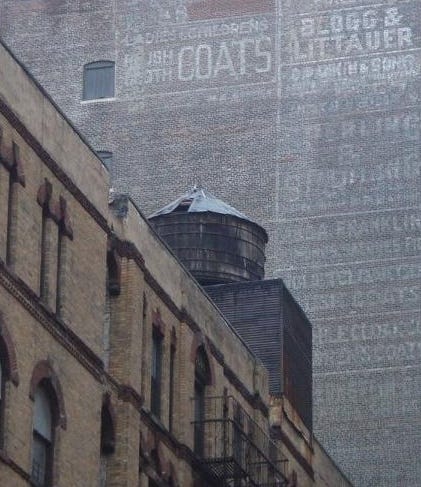
O blog New Type York fica catalogando 'artefatos tipográficos' de Nova York. São sinalizações de rua, nomes de prédio, placas de rua. O que for, onde for, para registrar todas as 'memoráveis e bonitas peças de tipografia' da cidade. Ainda está no comecinho, mas vale a pena acompanhar e, depois, acho que vai dar para usar o blog como guia de turismo tipográfico.